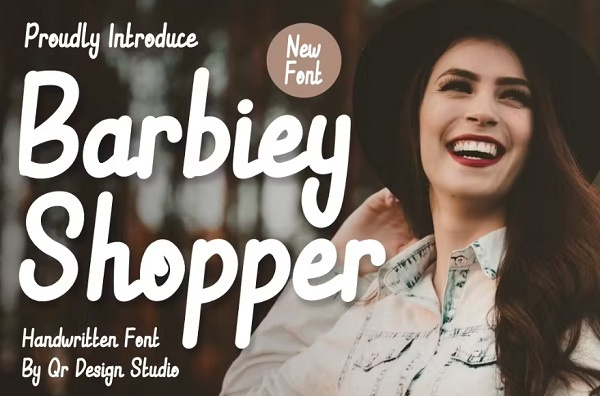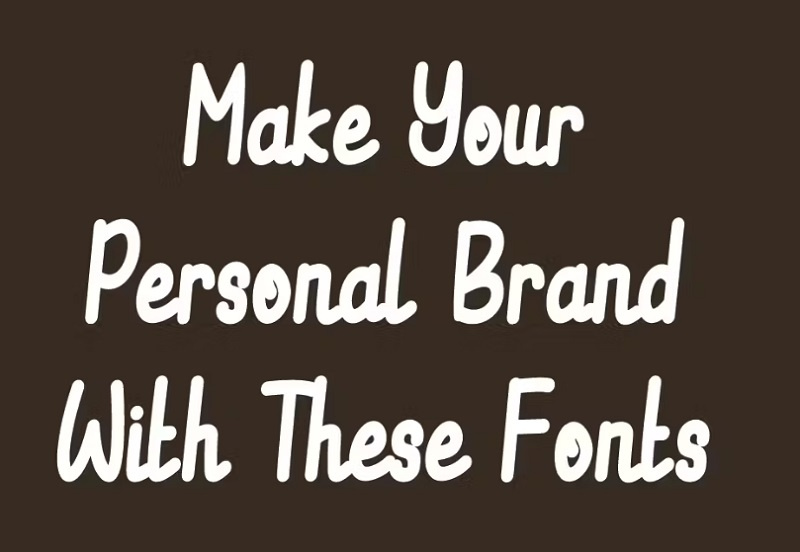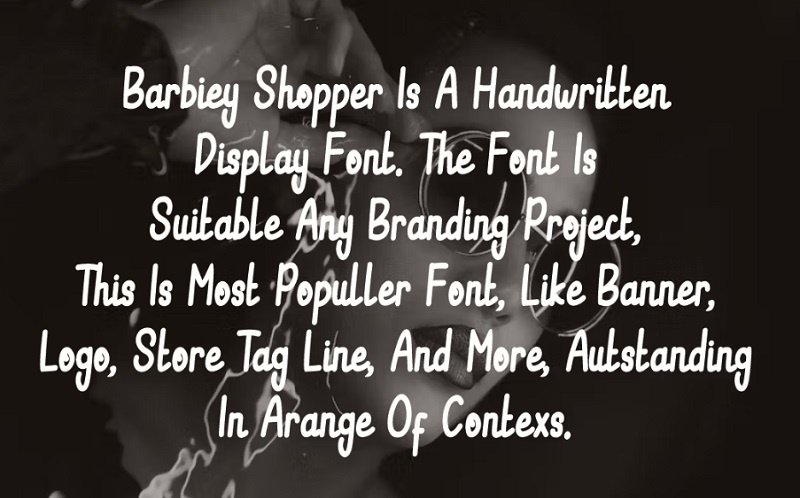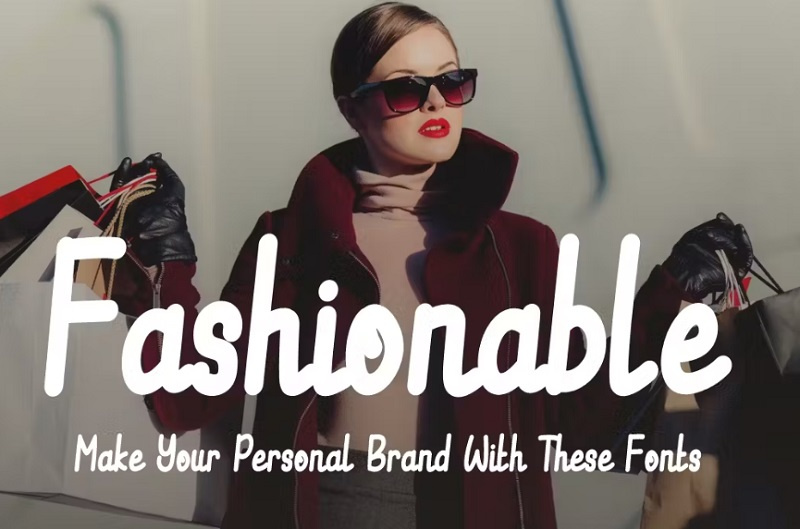
فونت انگلیسی Barbiey Shopper
فونت انگلیسی Barbiey Shopper یک فونت بسیار زیبا و کاربردی است. این فونت انگلیسی برای هر پروژه ای مانند برندسازی ، لوگو، غذا، پوستر و بسیاری موارد دیگر مناسب است. در ادامه با دانلود این فونت زیبا و مشاهده تصاویر آن از gfxdownload.ir با ما همراه باشید.